從事廣告招牌生產的耀華製作室扎根於新蒲崗,其接班人李健明從小就在舖頭「打躉」,小時候常與擔當招牌師傅的父親李威四出製作招牌。他憶述,在未有電腦字體的年頭,寫字師傅會先執筆揮毫,再將墨寶轉交招牌師傅加工製成廣告牌。當年,李父與書法家老友李漢合作無間,在區內留下不少得意之作。這些招牌不但烙下李氏父子在工作室的點滴,也盛載社區舊日的回憶。
膠片v.s.黃銅 招牌物料顯示社區特色
他認為,街頭招牌各具特色,大可從尺寸、製作方法、取材物料、顏色、字型,甚至招牌內容入手,觀者能窺探該區於不同年代的社區文化與生活狀態。「新蒲崗屬平民區域,多為街坊小生意,所以一般會用膠片或者鐵皮製作平價招牌,霓虹燈同黃銅招牌相對較少。相反西營盤海味街就有好多金漆招牌,而且通常有內外兩塊,反映嗰區應該比較富裕。」
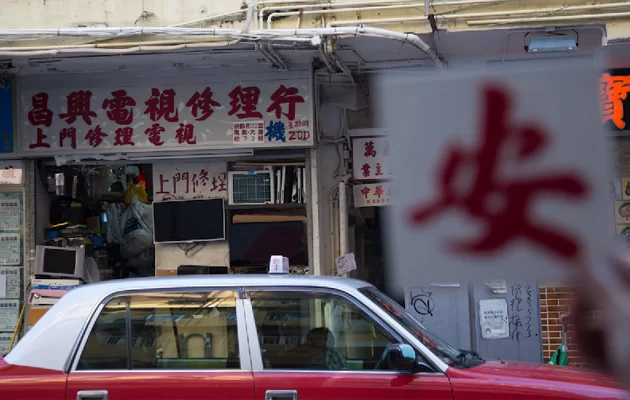
往昔小舖為求搶眼,會訂製顏色對比強烈的紅白招牌。「好多草根商戶為咗喺密集嘅市區環境做到最搶眼,招牌都會係白底紅字,而且盡量大大隻字撐盡招牌空位,因為以前啲人覺得字寫大隻啲會抵啲,如果啲字太細,會覺得我哋搵佢笨。」另外,招牌選材也能反映店家檔次。「大部分白底紅字都用膠片整,因為價格最平。俾得起錢嘅,就會揀霓虹或者黃銅等金屬物料。」位於大有街的建新疋頭公司就是區內少有的例子,選用金屬製北魏字款製作招牌,即使店舖被丟空十餘年亦未見有明顯破損,可見用料上乘,派頭十足,估計為富戶所擁有。
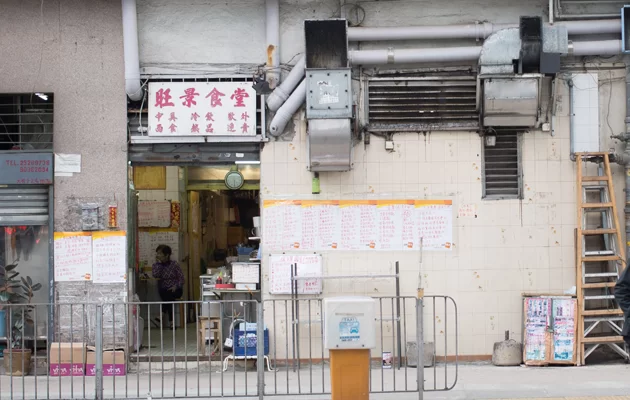
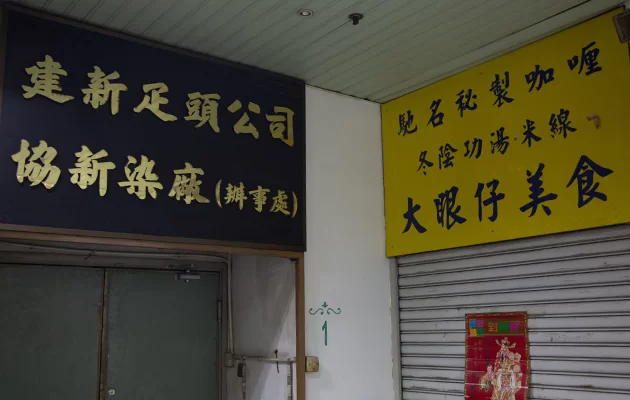
舊區慢發展 留住老招牌
跟着李健明沿着五芳街及大有街走,抬頭仰望,不難發現工廈外牆的鬼斧神工。「以前呢啲大廈外牆嘅大招牌通常都用水泥字,即係用水泥批盪批上去(將水泥漿塗抹在牆面,乾透成硬石屎後再加工雕剁成字)。因為日曬雨淋,咁整會耐用啲。呢種造法以前會比較多,依家真係買少見少。」來到立安工業大廈跟前,李健明停下腳步耐心解釋,「工廈喺1965年落成,一般水泥字係凸字比較常見,但呢個門牌係少有嘅凹雕石屎字,暫時喺新蒲崗只發掘到呢一個。」
但隨着社會對大廈用途的需求有所改變,此等做法已被續逐淘汰。他解釋,這種招牌需要師傅到現場雕畫製作,所需的工夫較多,人工與時間成本太高。為求減低成本及方便轉換,現時會傾向以「先製字、後安裝」的方法處理。製作方式的轉移,間接呈現了城市發展的動向。「新蒲崗無港鐵接駁,租金比觀塘等旺區平,店舖嘅流轉相對較慢,所以保留到老招牌嘅機會亦都大啲。如果你留意吓觀塘嘅地舖,會發現無咩舊招牌留低,因為商戶易手得快。」
招牌書寫方向 察知時代更迭
受西方文化影響,橫書漢字的書寫方向由從前的「右至左」演化成今天的「左至右」,而街頭招牌正是其中一種記錄了文字排列方向演進的媒介。「好似善美針織廠嘅招牌,就以比較傳統嘅方法排列。英文當然係左至右喇,但舊時中文會係由右至左寫番過去。雖然我記得細個喺新蒲崗見過一個英文由右至左寫嘅例子,不過嗰個招牌其實係做錯咗,行內當笑話咁睇。嗰個牌到2000年左右都仲喺嘅,但依家不復存在啦,好後悔當時無影低。」
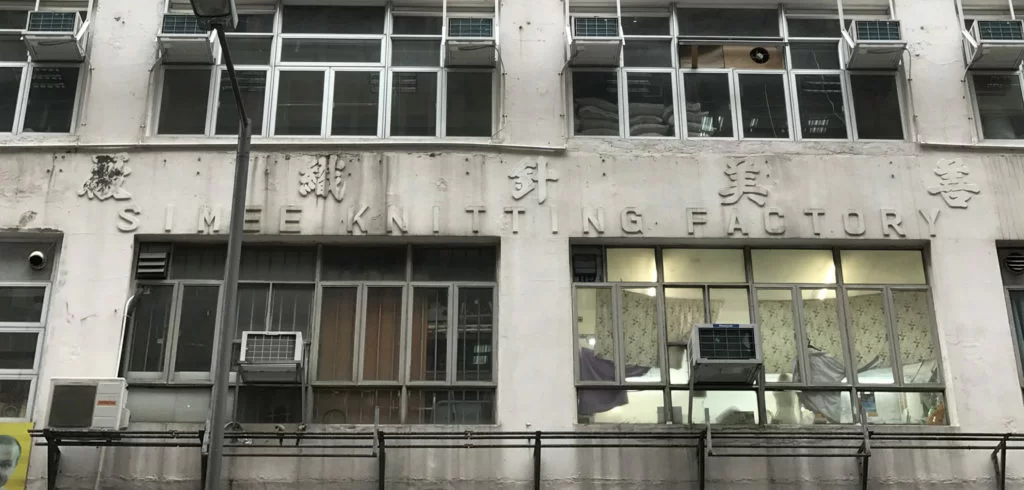
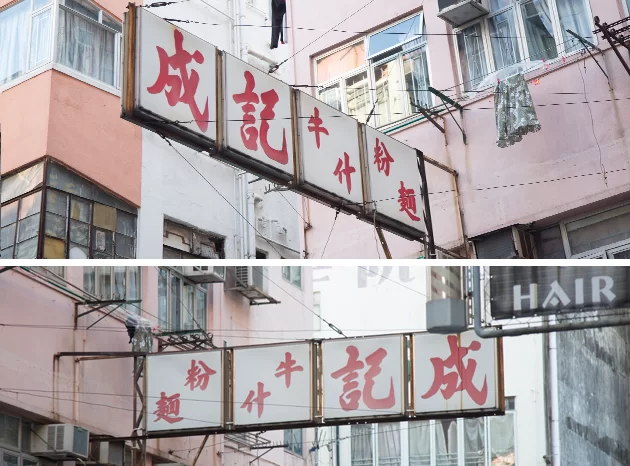
招牌款式多由寫字師傅拍板
坊間不少人覺得字體與行業性質有所關聯,李健明對此卻有所保留。「經過多年觀察,我覺得客戶從事嘅行業同佢哋招牌選用嘅字款其實未必有必然關係。第一,以前基層嘅商戶訂造時只會講低尺寸、顏色、內容等基本資料,對字體要求唔係太高;第二,舊時招牌造出嚟咩樣,係由招牌師傅決定。無電腦繪圖嘅年代,要靠人手起稿,每份稿都要俾錢。七十年代造霓招牌起草圖都幾貴㗎,睇一次要成一百蚊左右,唔係個個客都願意俾,所以好多時交貨前都無圖樣睇。而招牌師傅用咩字體、物料同顏色,其實好取決於同佢合作嗰位寫字師傅手字同埋客戶可以俾到幾多錢。」
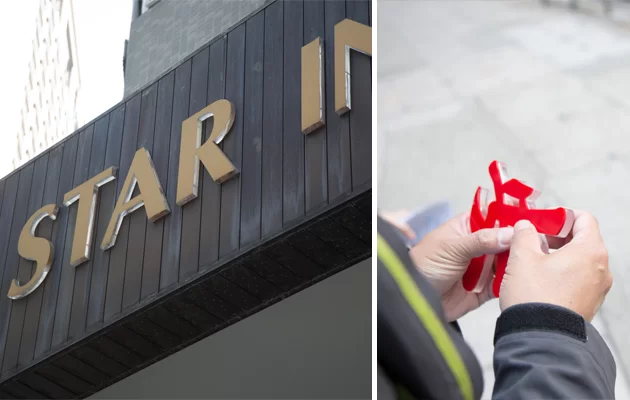
這些因素促使手寫招牌風格非常多樣化,單是手寫字體已是包羅萬象,形成本港獨有的街道景觀。「舊時每個寫字佬都識寫幾種唔同嘅中文書法字體,例如行書、草書、隸書或者楷書。依我觀察所見,區內用隸書寫嘅招牌唔多,因為搵寫字佬寫隸書係收得貴過楷書。當時寫楷書最平,所以楷書招牌特別多,望起上嚟比較平民化。」
再說,英文字母與數字原來亦暗藏有趣典故。「舊招牌上嘅英文字好多時係由招牌佬畫上去,佢哋通常都袋定一、兩種英文字款旁身。而數目字又會同英文字唔同款喎,點解呢?嗰時我阿爸就話係因為佢哋唔識寫數字,咁就直接喺日曆度copy。」他又指,很多招牌師傅為了把中、英文字左右對齊,會刻意把英文字「拉長㩒扁」,縮窄字距。雖然顯得密密麻麻,但比起形式化的電腦字,卻多了一份本土風情。
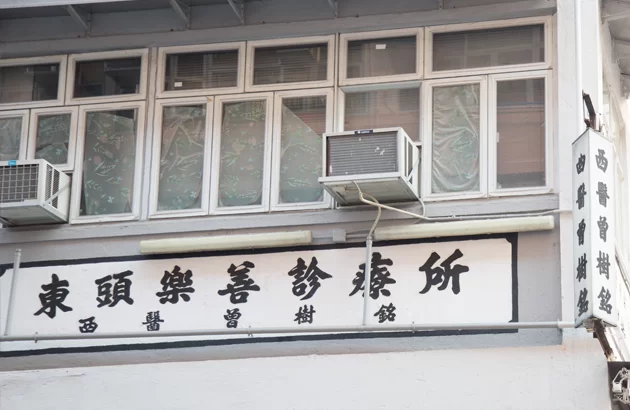
電話號碼與用字 揭露「年齡」秘密
想知廣告牌於哪個年代製成,難度與查探妙齡女子於何年出世一樣,難以考究。然而寫上電話號碼的緯綸電器(五方街23號)門牌,卻意外露出馬腳。在1960至80年代,本港的電話以地區字頭制度分成港、九、新界三區,加上六位數字的電話號碼,合共由七個數目組成。其後,字頭分區制於1990年被廢除,電話號碼劃一保留七位數字。直到1995年起,電話號碼再添一字,成了流通至今的八位數字。「究竟個牌幾時造呢?線索就係個電話號碼。按照咁嘅推論,呢個招牌計埋最少都有廿幾年歷史,即係代表呢間舖起碼有廿幾年無轉換過租戶,或者佢本身就係業主。」他感慨如今要在香港地找個屹立二十年的地方,絕對有難如登天之感。
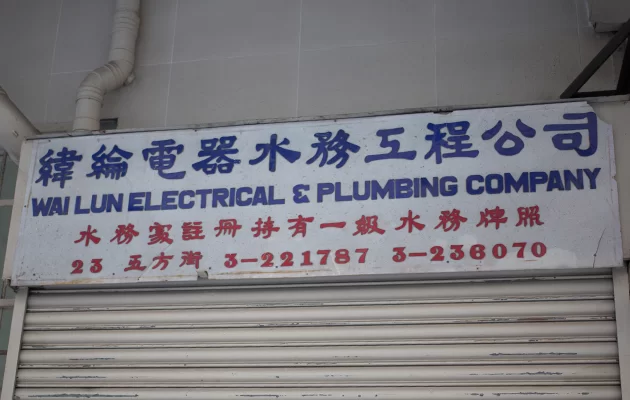
舊式招牌另一個特點是內容直白,而且老一輩的店主總以學生交作文的邏輯造牌,寫得幾多得幾多。即使是八、九十年代常見的鮮紅「痔」字招牌也不忘補筆幾句玩硬銷。牌的右上方寫有《基本法》,李健明推測此招牌製於中英聯合聲明發表的年代。他謂招牌用字某程度可以透露時代精神,「嗰個年代咩都講基本法,因為係當時社會一個熱門話題,好多舖頭都攞呢樣嘢嚟玩,所以都反映到嗰個時代嘅嘢。」
耀華製作室接班人,亦是「李伯伯街頭書法復修計劃」的負責人,致力將街頭書法家李漢的手寫筆迹整理集結成完整的「李漢港楷」電腦字體。